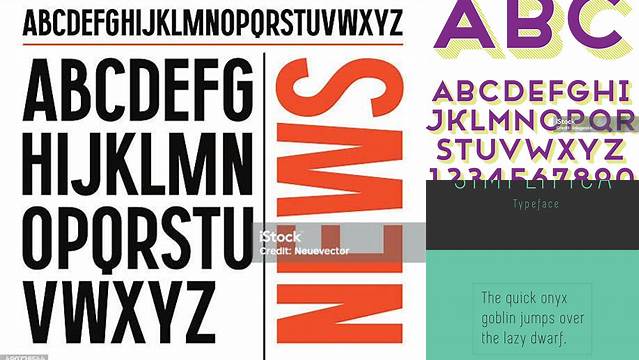
Sans Serif Font Gratis: Unduh & Gunakan Di Desainmu
Sans serif fonts telah menjadi tulang punggung desain modern, menawarkan estetika yang bersih, mudah dibaca, dan serbaguna. Jika kalian adalah seorang desainer, pembuat konten, atau sekadar seseorang yang menyukai tipografi yang bagus, kalian pasti sudah tidak asing lagi dengan keindahan sans serif fonts. Untungnya, ada banyak pilihan sans serif font free download yang tersedia, memungkinkan kalian untuk bereksperimen dengan berbagai gaya tanpa mengeluarkan biaya sepeser pun. Dalam artikel ini, kita akan membahas seluk-beluk sans serif fonts, menjelajahi mengapa mereka sangat populer, dan memandu kalian untuk menemukan unduhan gratis terbaik yang sesuai dengan kebutuhan desain kalian.
Apa Itu Sans Serif Font? Mengapa Begitu Populer?
Sans serif fonts adalah jenis huruf yang tidak memiliki serif, atau garis kecil dekoratif, yang menonjol dari ujung setiap karakter. Kata "sans serif" berasal dari bahasa Prancis, yang berarti "tanpa serif." Berbeda dengan serif fonts, seperti Times New Roman atau Georgia, yang memiliki serif, sans serif fonts menampilkan tampilan yang lebih minimalis dan modern. Keterbacaan mereka dalam berbagai ukuran dan media, bersama dengan kesederhanaannya, berkontribusi pada popularitas mereka yang luas. Sans serif fonts menawarkan tampilan yang bersih dan kontemporer, yang membuat mereka menjadi pilihan yang sangat baik untuk berbagai aplikasi desain. Dari logo dan tajuk utama hingga teks tubuh dan antarmuka digital, fleksibilitas mereka menjadikannya pilihan populer di kalangan desainer dan merek di seluruh dunia. Gaya bersih dan lugas mereka sangat cocok untuk menyampaikan pesan yang jelas dan ringkas, membuatnya ideal untuk judul, subjudul, dan materi branding. Selain itu, sans serif fonts sering dianggap lebih mudah dibaca di layar, menjadikannya pilihan yang sangat baik untuk desain digital, seperti situs web dan aplikasi seluler. Mereka juga sangat baik untuk penggunaan di media cetak karena kesederhanaan dan keterbacaan mereka. Tentu saja, sans serif fonts juga memiliki kekurangan. Beberapa desainer mungkin menganggapnya terlalu datar atau kurang memiliki karakter dibandingkan dengan serif fonts, yang dapat menambahkan lebih banyak kepribadian pada desain. Namun, secara keseluruhan, sans serif fonts tetap menjadi pilihan yang tak ternilai dalam desain modern. Berbagai macam gaya yang tersedia, dari sans serif fonts geometris dan bersih hingga sans serif fonts yang lebih ramah dan manusiawi, memastikan bahwa ada font yang sesuai dengan setiap proyek dan gaya desain. Dalam dunia desain, sans serif fonts tetap menjadi pilihan yang tak ternilai, menawarkan keseimbangan yang sempurna antara kesederhanaan, keterbacaan, dan fleksibilitas.
Keuntungan Menggunakan Sans Serif Fonts
Sans serif fonts menawarkan beberapa keuntungan dibandingkan dengan jenis huruf lainnya, menjadikannya pilihan yang menarik untuk berbagai aplikasi desain: Keterbacaan yang sangat baik: Sans serif fonts sering dianggap lebih mudah dibaca, terutama dalam ukuran yang lebih kecil dan di layar. Ketiadaan serif yang rumit membuat mata lebih mudah memproses huruf, sehingga meningkatkan keterbacaan, terutama pada layar digital. Ini sangat penting untuk desain web, aplikasi seluler, dan materi digital lainnya di mana keterbacaan adalah kunci. Tampilan modern dan bersih: Sans serif fonts memberikan tampilan yang bersih dan modern yang sesuai dengan tren desain saat ini. Kesederhanaan mereka memberikan kesan yang segar dan kontemporer yang dapat membuat desain kalian terasa relevan dan menarik. Serbaguna: Sans serif fonts sangat serbaguna dan dapat digunakan dalam berbagai aplikasi desain, mulai dari branding dan logo hingga teks tubuh dan tajuk utama. Mereka bekerja dengan baik dalam berbagai konteks, menjadikannya pilihan ideal untuk proyek yang membutuhkan fleksibilitas dan adaptasi. Ideal untuk digital: Dengan semakin banyaknya konsumsi konten secara online, sans serif fonts menjadi pilihan yang tepat untuk desain digital. Sans serif fonts sangat baik untuk tampilan layar karena keterbacaan mereka, yang penting untuk pengalaman pengguna yang baik. Ketersediaan luas: Banyak sans serif fonts tersedia secara gratis, membuatnya mudah diakses oleh semua orang, terlepas dari anggaran. Sans serif fonts sering kali menawarkan berbagai bobot dan gaya, memberikan lebih banyak opsi untuk kebutuhan desain kalian.
Font yang Direkomendasikan untuk Unduhan Gratis
- Lato: Lato adalah sans serif fonts serbaguna dan ramah yang dirancang oleh Łukasz Dziedzic. Dengan bentuk yang seimbang dan karakter yang sangat baik, ia cocok untuk berbagai aplikasi desain, termasuk teks tubuh dan judul. Tersedia di Google Fonts.
- Open Sans: Open Sans adalah sans serif fonts yang sangat mudah dibaca dan dirancang oleh Steve Matteson. Ia dikenal karena keterbacaannya yang sangat baik di layar, menjadikannya pilihan yang sangat baik untuk desain digital. Tersedia di Google Fonts.
- Montserrat: Montserrat adalah sans serif fonts geometris yang terinspirasi oleh arsitektur Buenos Aires. Ia menawarkan tampilan modern dan bersih dan merupakan pilihan yang bagus untuk branding, logo, dan judul. Tersedia di Google Fonts.
- Raleway: Raleway adalah sans serif fonts elegan dengan berbagai bobot dan gaya. Ia cocok untuk berbagai aplikasi desain dan menawarkan tampilan yang canggih dan kontemporer. Tersedia di Google Fonts.
- Roboto: Roboto adalah sans serif fonts yang dikembangkan oleh Google. Ia dirancang untuk keterbacaan yang sangat baik di berbagai perangkat dan resolusi. Ini adalah pilihan yang sangat baik untuk antarmuka pengguna dan desain digital.
Cara Menggunakan Sans Serif Font dalam Desain Kalian
Setelah kalian mengunduh sans serif font free download yang sempurna, inilah beberapa tips tentang cara menggunakannya secara efektif dalam desain kalian:
Pilih font yang tepat untuk proyek kalian
Pertimbangkan tujuan desain, audiens, dan merek kalian. Pilih sans serif fonts yang melengkapi pesan kalian dan sesuai dengan gaya desain kalian. Misalnya, jika kalian menginginkan tampilan yang bersih dan modern, pertimbangkan font geometris. Jika kalian menginginkan tampilan yang lebih ramah dan mudah didekati, pilih sans serif fonts dengan bentuk yang lebih melengkung.
Kesimpulan
Sans serif fonts menawarkan keunggulan yang tak terbantahkan dalam dunia desain modern. Keterbacaan yang unggul, tampilan bersih, dan fleksibilitas menjadikannya pilihan yang sangat baik untuk berbagai aplikasi, dari desain web hingga branding. Dengan banyaknya sans serif font free download yang tersedia, kalian dapat dengan mudah menemukan font yang sempurna untuk proyek desain kalian tanpa mengeluarkan biaya sepeser pun. Manfaatkan sumber daya yang disebutkan di atas, bereksperimenlah dengan berbagai gaya, dan buat desain yang menakjubkan dengan sans serif fonts pilihan kalian. Jangan ragu untuk menjelajahi berbagai pilihan, unduh gratis, dan mulai berkreasi hari ini! Ingatlah untuk selalu memeriksa lisensi font untuk memastikan kalian menggunakannya dengan benar. Selamat mendesain!